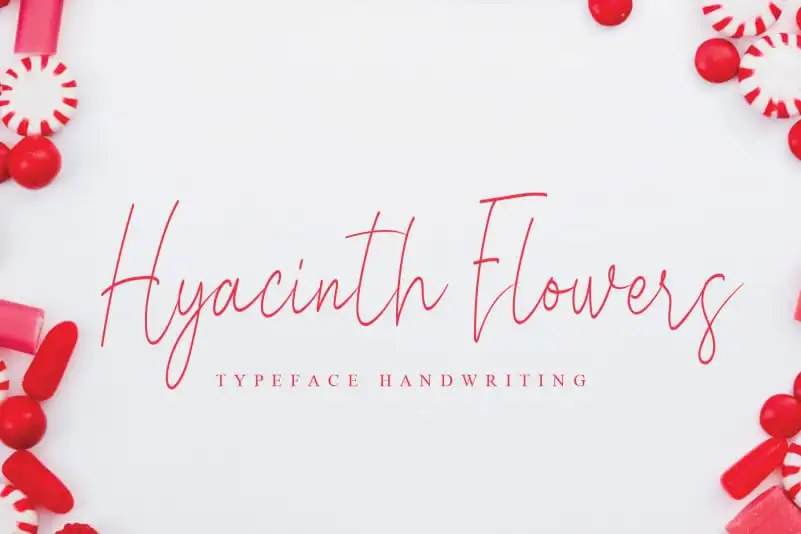
Hyacinth Flowers Handwritten Font – Download Grátis
A Hyacinth Flowers Handwritten Font é uma deliciosa tipografia escrita à mão com traços finos. Ela transmite sentimentos delicados e românticos, adequada para aprimorar ideias criativas. Seu aspecto suave irá adicionar um toque de luminosidade a qualquer projeto. Ideal para designs pessoais ou que buscam uma atmosfera levemente flutuante e encantadora, essa fonte é perfeita para aqueles apaixonados por estilos delicados e românticos, que não hesitam em utilizar suas nuances únicas na sua próxima criação. Seja para criar um card personalizado ou uma capa de livro, esta fonte tem tudo o que você precisa para fazer seus projetos brilharem.